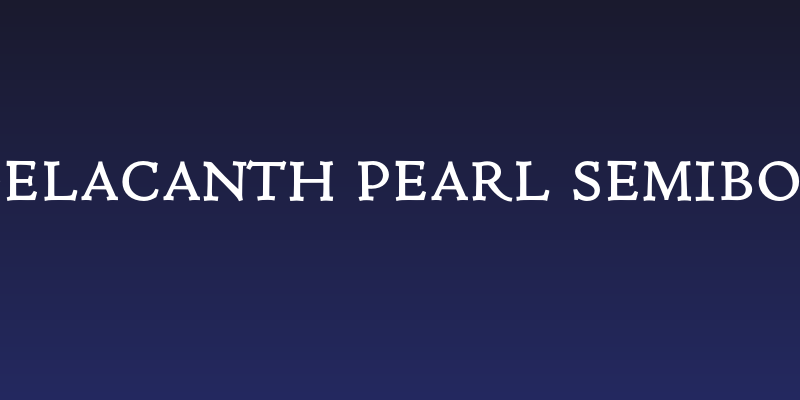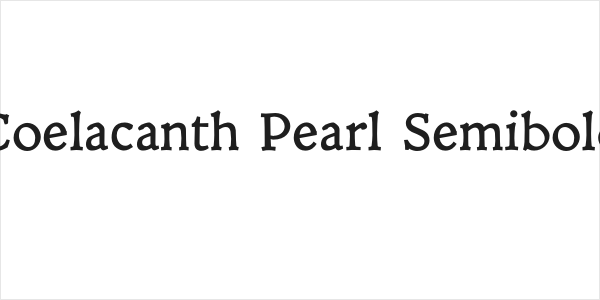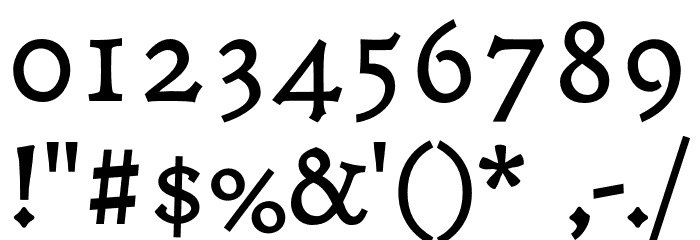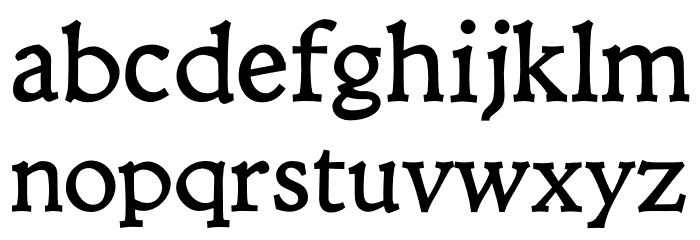
Coelacanth Pearl Semibold Font
| Caso de uso | Headlines, Body text, Editorial design |
| Projetos propostos | This font is perfect for projects that require a touch of elegance and tradition, such as book covers, formal invitations, and editorial layouts. |